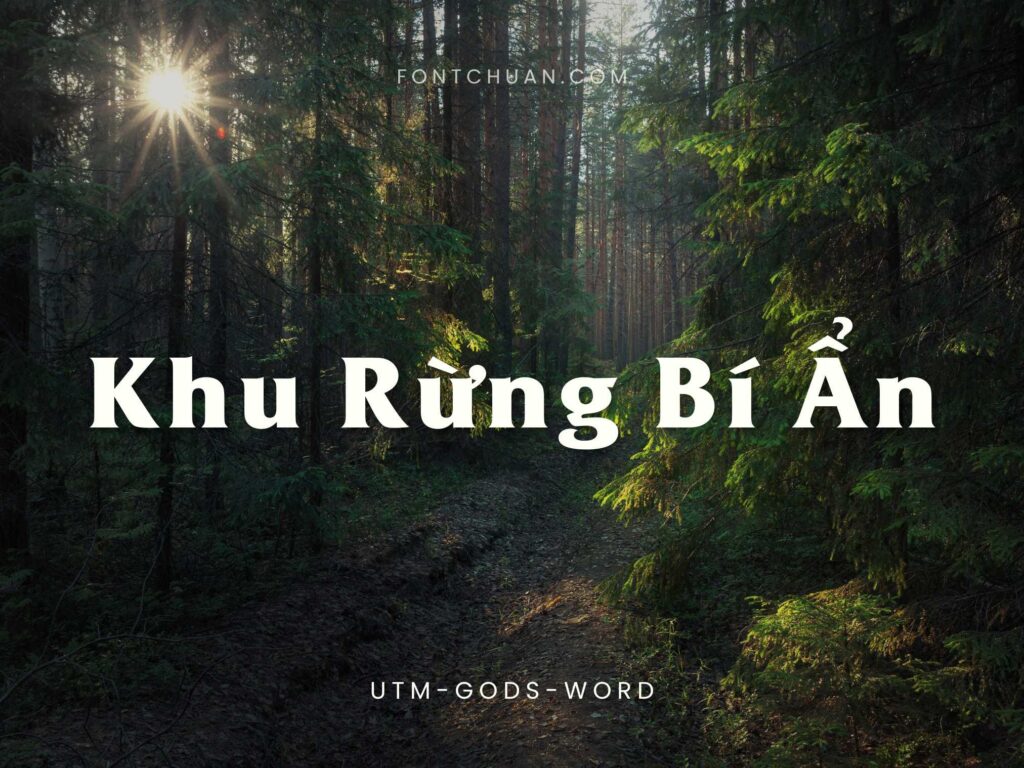
Font UTM God’S Word Việt Hóa
UTM God’s Word là một font chữ serif được thiết kế bởi Michael Đinh Kiên, mang đến sự kết hợp tinh tế giữa truyền thống và hiện đại. Font này đã được Việt hóa bởi Thiên Minh, hỗ trợ tiếng Việt và hơn 200 ngôn ngữ khác, giúp mở rộng khả năng ứng dụng trong thiết kế đa dạng. Thành viên của Font Chuẩn đã sưu tầm và chia sẻ font này nhằm đáp ứng nhu cầu bạn đọc, cung cấp nguồn tham khảo chất lượng và ứng dụng thực tế vào các dự án thiết kế.
UTM God’s Word cũng là một Font DisplayFont sinh nhật độc đáo, mang đến sự kết hợp tinh tế giữa nét cổ điển và hiện đại. Với các đường nét sắc sảo nhưng vẫn mềm mại, font này phù hợp để thiết kế thiệp mừng, banner, tiêu đề nổi bật hay các ấn phẩm sinh nhật, giúp tạo cảm giác vừa trang trọng, vừa vui tươi và thu hút.
Về đặc điểm thiết kế, UTM God’s Word sở hữu cấu trúc chữ với các đường nét sắc sảo, độ tương phản cao và độ dày trung bình, tạo cảm giác trang trọng và dễ đọc. Font này phù hợp cho các thiết kế liên quan đến tôn giáo, văn học, giáo dục và các dự án nghệ thuật. Các ngành nghề như giáo dục, quảng cáo, ẩm thực và thiệp cưới có thể tận dụng font này để tạo nên sự khác biệt và thu hút trong các ấn phẩm của mình.